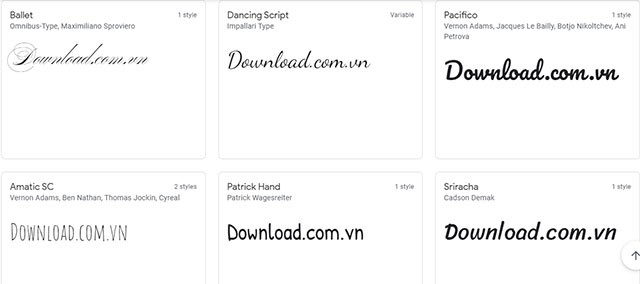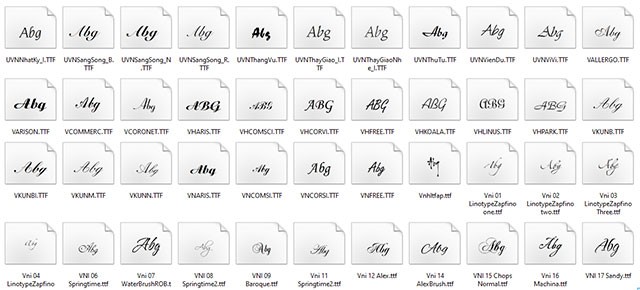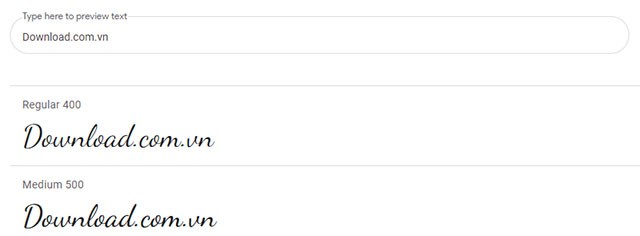
Khám Phá Bộ Font Chữ Tiếng Việt Mô Phỏng Chữ Viết Tay Miễn Phí
Bộ font chữ tiếng Việt này là một sưu tập các kiểu chữ được thiết kế để mô phỏng nét chữ viết tay truyền thống, hoàn toàn miễn phí cho hệ điều hành Windows.
Với bộ font này, người dùng có thể tự do sáng tạo ra những văn bản độc đáo, mang phong cách đánh máy gần gũi, thân thiện và thể hiện cá tính riêng.
Mặc dù Bộ Font tiếng Việt đầy đủ cũng bao gồm một số font chữ viết tay, nhưng bộ sưu tập này mang đến sự đa dạng và lựa chọn phong phú hơn cho người dùng.
Đặc biệt, đây là một công cụ hữu ích cho các giáo viên, giúp họ dễ dàng viết mẫu chữ cho học sinh.
Font Chữ Viết Tay: Nguồn Cảm Hứng Cho Thiết Kế
Sự sáng tạo luôn là yếu tố then chốt trong lĩnh vực thiết kế, và bộ font chữ viết tay này chính là nguồn cảm hứng bất tận cho những người làm nghề.
Thay vì sử dụng các font chữ đơn giản, quen thuộc, bộ font này mang đến một làn gió mới, tạo nên sự khác biệt và thu hút.
Dù không mang tính nghệ thuật cao như Font chữ thư pháp , font chữ viết tay vẫn tạo được thiện cảm và sự gần gũi với người xem.
Font Chữ Google Sans và Sự Đa Dạng Trong Thiết Kế
Google cũng đã phát triển một bộ font chữ tiếng Việt riêng, mang phong cách đơn giản và hiện đại, dựa trên Font chữ Google Sans.
Bộ font này bao gồm 14 định dạng khác nhau với những nét chữ viết tay uyển chuyển, hứa hẹn sẽ chinh phục mọi độc giả.
Vẻ đẹp của nét chữ viết tay luôn có sức hút đặc biệt, và mỗi font chữ trong bộ sưu tập này đều mang một dấu ấn riêng.
Bạn có thể thỏa sức sáng tạo ra những bản vẽ, bản thiết kế độc đáo để thể hiện phong cách cá nhân.